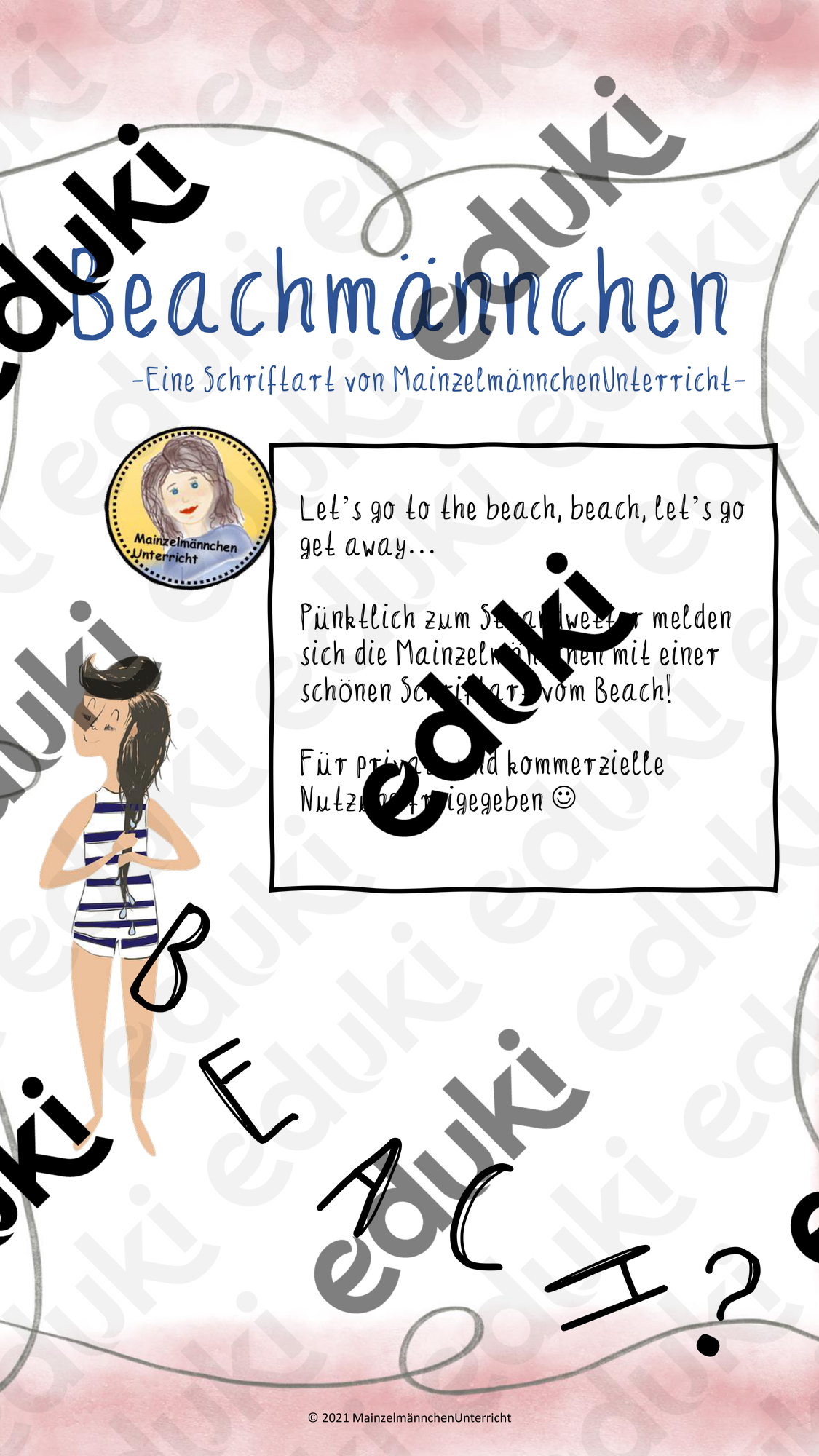
selbst erstellte Schriftarten - Beachmännchen - ein sommerlicher Font - MainzelmännchenUnterricht - Deckblatt
Schöner Font für Arbeitsblätter. Kommerzielle Nutzung erlaubt.
Beachmännchen - ein sommerlicher Font